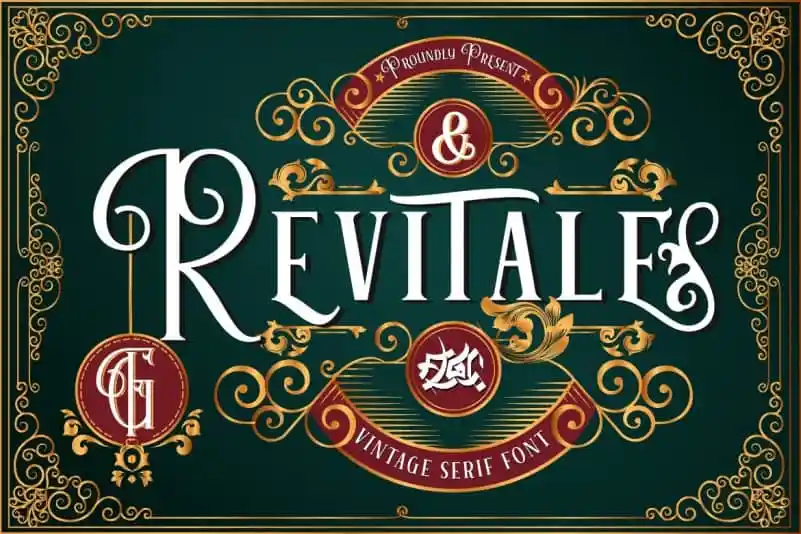
Revitale Display Font – Download Grátis
A Revitale Display Font é uma seleção diversificada de tipografias inspirada nas lendas reais de antigos reinados. Desenhada pelo designer FallenGraphic Studio, a fonte traz elementos vívidos e elegantes que mantêm um visual consistente. Essa fonte perfeita para a marca, cabeçalhos, assinaturas, logotipos, blogs, convites de casamento, camisetas, letras finais, materiais promocionais, sinalizações, rótulos, notícias e cartazes. A Revitale Display é uma escolha excelente para diversas aplicações visuais onde a elegância combinada com criatividade se encaixa perfeitamente.